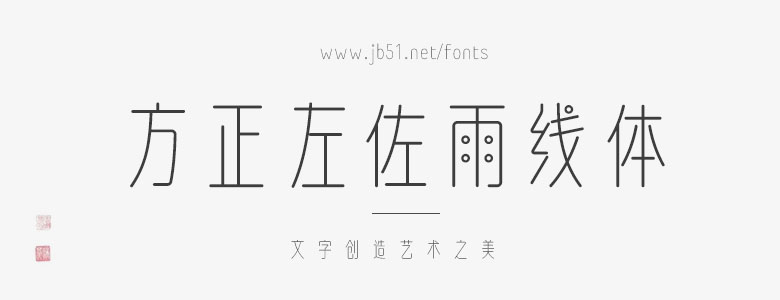
雨線體Rainline,筆畫為等線形式,結(jié)構(gòu)試圖在書寫與幾何之間找到平衡點(diǎn),字面和曲線的風(fēng)格參考小篆,偏瘦長(zhǎng),接近黃金比。點(diǎn)似雨滴,線如雨簾,清新纖婉。風(fēng)格關(guān)鍵詞:知性、美妝、護(hù)膚、時(shí)尚、精致、科技產(chǎn)品、水、新媒體、互聯(lián)網(wǎng)等。
作者左佐,是左佐工作室主理人、中國(guó)中文信息學(xué)會(huì)會(huì)員、深圳平面設(shè)計(jì)協(xié)會(huì)會(huì)員;編著《治字百方》、《排版的風(fēng)格》;2014年度十佳新銳設(shè)計(jì)師之一;中國(guó)十大最具靈感年輕設(shè)計(jì)師之一。先后曾獲得GDC設(shè)計(jì)獎(jiǎng)文字設(shè)計(jì)類銀獎(jiǎng)、海峽兩岸最美的書特別推薦獎(jiǎng)、站酷獎(jiǎng)字形類金獎(jiǎng)、站酷十年成就獎(jiǎng)獲得者。